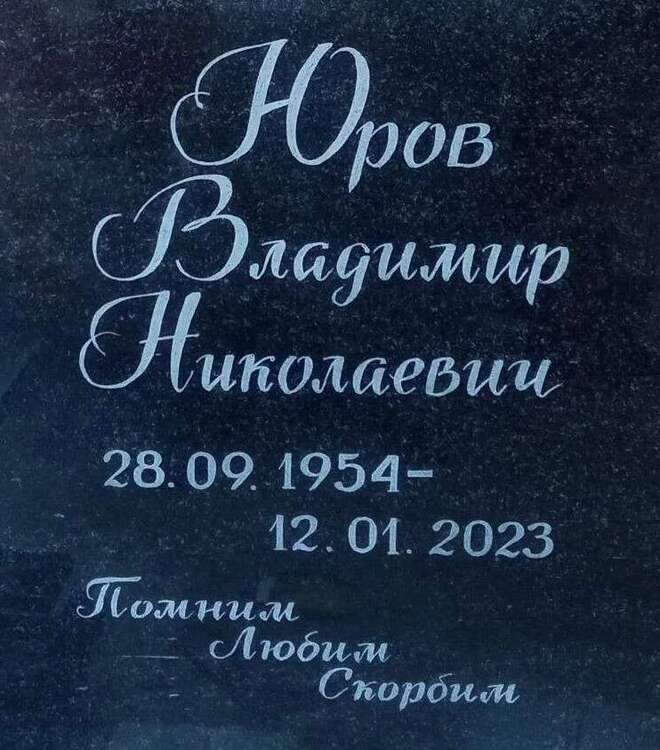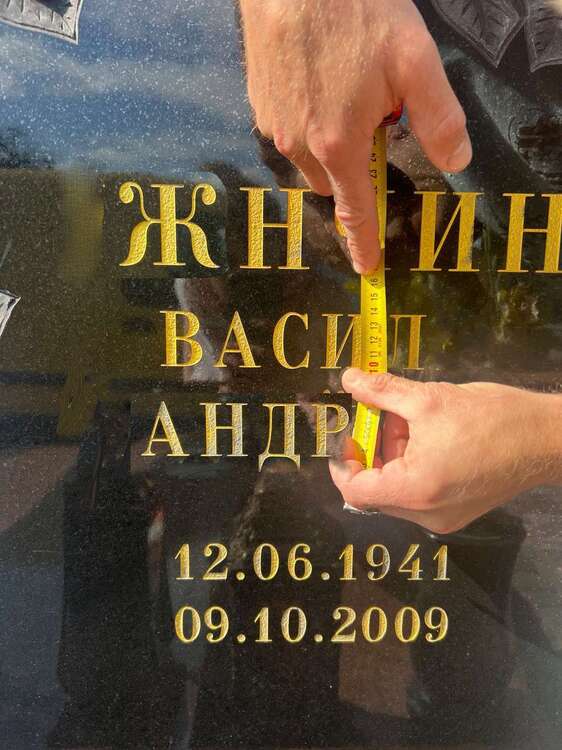
алена Опубликовано 22 мая, 2024 (изменено) Dutch Bold Italic Droid Serif Bold Italic Посмотрите, по-моему похоже a_BodoniNova BoldItalic - этот точно Изменено 22 мая, 2024 пользователем алена 1
александр577 Опубликовано 23 мая, 2024 Привет всем может кто знает что за шрифт такой в поисковике найти не могу
fenix Опубликовано 23 мая, 2024 (изменено) Помогите найти шрифт-Ы пожалуйста Изменено 23 мая, 2024 пользователем fenix
алена Опубликовано 31 мая, 2024 @александр577 Bolero script @fenix Snell Roundhand Black 1
fenix Опубликовано 31 мая, 2024 @алена Спасибо Подскажите, пожалуйста, что за шрифт?
kamnerez Опубликовано 31 мая, 2024 @fenix https://fonts-online.ru/fonts/monotype-corsiva 2
алена Опубликовано 31 мая, 2024 (изменено) @fenix Poetica Chancery Нет не он. Похож просто..... Изменено 31 мая, 2024 пользователем алена 1
Kim Опубликовано 1 июня, 2024 20 часов назад, kamnerez сказал: @fenix https://fonts-online.ru/fonts/monotype-corsiva Он самый 20 часов назад, fenix сказал: @алена Спасибо Подскажите, пожалуйста, что за шрифт? https://fonts-online.ru/fonts/monotype-corsiva 2
алена Опубликовано 6 июня, 2024 @fenix Это ручник бил., 100 % . А они часто от балды шрифт делают. Компьютерного шрифта такого в природе нет. 1
SenileDust Опубликовано 6 июня, 2024 Здравствуйте, добрые люди! Помогите пожалуйста найти название шрифта.
Crossbreed Опубликовано 6 июня, 2024 @SenileDust Это ручная работа! Именно эту же фотку мне приносили в телефоне и просили этот шрифт!))) В итоге в заказе был другой!
fenix Опубликовано 9 июня, 2024 @алена жалко, а примерный хотя бы чтобы по стилизации подходил, есть такой в природе... @SenileDust тоже весьма интересный шрифт для эпитафии, жаль что в компьютерном варианте нет...
алена Опубликовано 9 июня, 2024 @fenix Adventure Вот еще, может что-то подойдет. Обсудите с клиентами. 1
Starche Опубликовано 13 июня, 2024 Похож на Таймс нью роман, только всё заглавные.
алена Опубликовано 13 июня, 2024 @puzh Это ручник. У них есть свойство видоизменять шрифты. Художники - личность творческая)) Вот шрифт "4" только другая. Century
Калуга Опубликовано 13 июня, 2024 Похож на Bodoni, только 1 немного изменена.